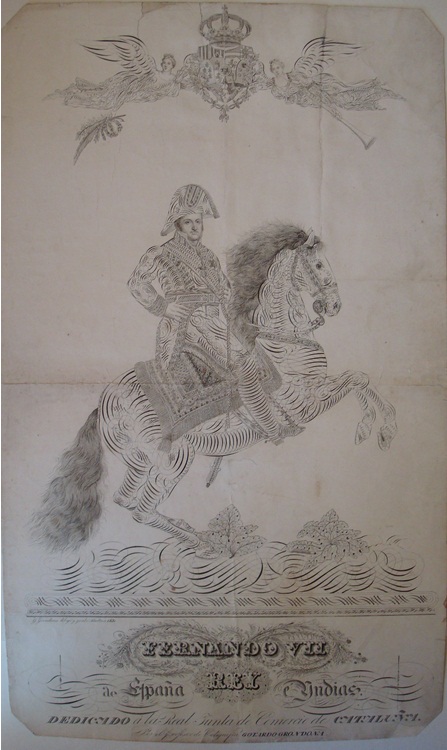
Detalle de una Capital de Torío de la Riva |
CONSIDERACIONES
En estos artículos describiré obras publicadas a partir de 1800 hasta 1900 algunas simples cuadernos de muestras otras tratados de escribir. La bibliografía del S.XIX a sido poco estudiada, la única referencia la encontramos en la bibliografía general de Palau y Dulcet, "Librero Hispana-Americano" y en el diccionario Biográfico y Bibliográfico de los calígrafos españoles de Cotarelo y Mori, (ver artículo anterior de bibliografías sobre caligrafía), así pues las descripciones de los ejemplares en algún caso no son completas ya que muchas veces no vieron los ejemplares descritos.
Los libros del S. XIX son tan raros o a veces mucho mas raros que los del siglo anterior ya que se publicaron como efímeras obras para los colegios y la mayoría eran de usar y tirar (Cuadernillos de muestras o cuadernillos de teoría caligráfica) para describirlo mas llanamente, aun así hay grandes y bonitos libros mas pensados para profesionales de imprenta o simplemente mejor editados.
Este siglo se inauguró con la redición de la obra de T. Torio de la Riva "Arte de escribir..." solo hacia cuatro años que se publicó la 1ª edición y a causa de su gran éxito se reditó en dos formatos diferentes veámoslos:
TORIO DE LA RIVA, TORQUATO.
ARTE DE ESCRIBIR CON REGLAS Y CON MUESTRAS según la doctrina de los mejores autores...
Madrid 1802 Viuda de Joaquín Ibarra
Folio, 29 x 20 cm, papel de gran calidad y amplios márgenes, portada dibujada por L. Paret y grabada por B. Ametller + + XXVIII páginas que incluyen: gravado del Conde de Trastámara, Dedicatoria, Privilegio, Introducción, Listado alfabético de personalidades y Tabla (índice) + 418 páginas que aparte incluyen 58 láminas numeradas de muestras caligráficas, no incluye página de erratas, solamente una mención al tema.
Este libro fue de gran éxito y se utilizó como base para aprender no solo caligrafía sino aritmética ortografía y buenas costumbres. En esta edición corrige erratas y amplia las noticias sobre algunos calígrafos que no figuraban en la primera, también nos expone el privilegio de 1801 que obtuvo por el éxito de la primera edición. Rápidamente pensará en imprimir un formato mas barato en 4º para atender las demandas de esta obra que parece ser fueron muchas.
Conde de Trastámara |
4º, 21 x 15 cm. Portada dibujada por L. Paret y grabada por B. Ametller + XXXI páginas + 445 páginas + 58 láminas de muestras caligráficas. Este formato no incluye el retrato del Conde de Trastámara.
Bellas capitales Adornadas y algunas letras de Adorno:
Algunos ejemplares de la segunda edición en los dos formatos presentan una variación en la lámina 36 del texto y fecha de 1803, es una lámina en fondo negro la plancha de la cual seguramente se estropeo del uso. Parece ser que se fabricó otra plancha parecida con texto parecido y también de Torio de la Riva. que sustituyó la dañada. El papel en general es de menor calidad que las anteriores ediciones y este fue el tiraje que se utilizó más en las escuelas y el último que se imprimió.
Podríamos decir pues que si bien lleva la fecha de 1802 algunos ejemplares se tiraron ya en 1803.
1ª Lámina, 1ªEd. y 2ª Ed. |
Lámina sustitutoria en algunos ejemplares de la 2ª Ed. 1803 |
Torio de la Riva es el autor más importante de final del S XVIII y su influencia durará dos décadas mas entrado ya el XIX.
FELIU DE LA VIRGEN MARÍA, P. JACINTO.
ELEMENTOS DE GRAMÁTICA CASTELLANA ORTOGRAFÍA Y CALOGRAFÍA con la COLECCIÓN DE MUESTRAS DE LETRA BASTARDA...
Palma de Mallorca, 1813, Imp. Felipe Guasp.
4º menor, 50 páginas numeradas que incluyen la portada + Portada de la Colección de láminas + las siete láminas escritas por el P. Jacinto Feliu y grabadas por Máximo Cipriano Maré en Mallorca, con la misma fecha 1813, numeradas del (1a) al (7a). Primera y única edición.
El P. Jacinto Feliu de las Escuelas Pías parece que ejerció en Cataluña y en las Baleares Siguiendo la tradición de los mejores calígrafos publica este pequeño libro.
Según dice Cotarelo y Mori, el P. Jacinto fue seguidor de la escuela de Torio.
Este pequeño libro es difícil de encontrar.
NUEVA COLECCIÓN DE MUESTRAS ORIGINALES DEL CARÁCTER BASTARDO ESPAÑOL á LA YNGLESA.
Madrid?, 1817. Sin Editor.
4º apaisado, consta de 16 láminas que incluyen la portada que también esta grabada.